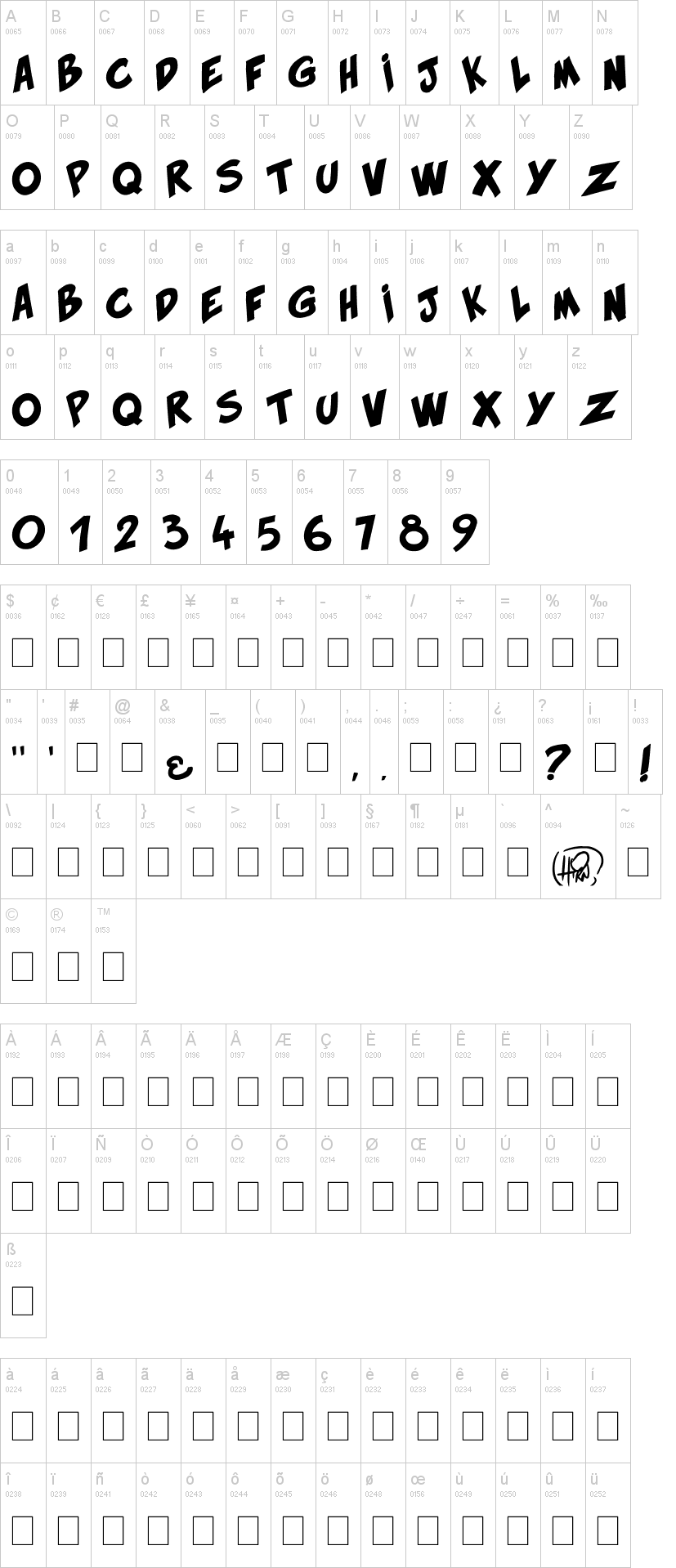
Note of the authorTypo onomatopée bd réaliste.
Définir l'approche à -100 pour l'effet escompté.
Realistic comic onomatopoeia typo.
Set the approach to -100 for the desired effect.